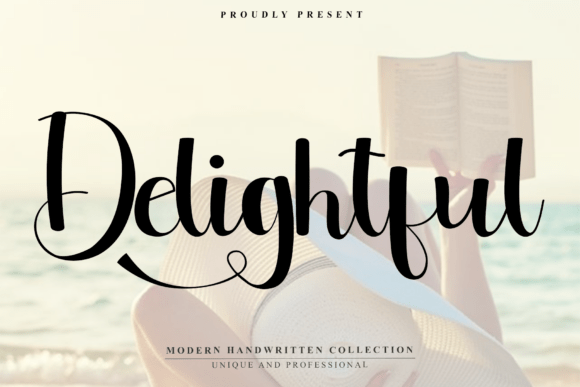
Delightful
適切なデザイン要素を見つけるのは難しい場合がありますが、Delightfulは作品を即座に引き立てる優れたコレクションを提供します。
POD(オンデマンド印刷)製品、結婚式の招待状、またはソーシャルメディアのグラフィックを作成している場合でも、Delightfulは理想的です。